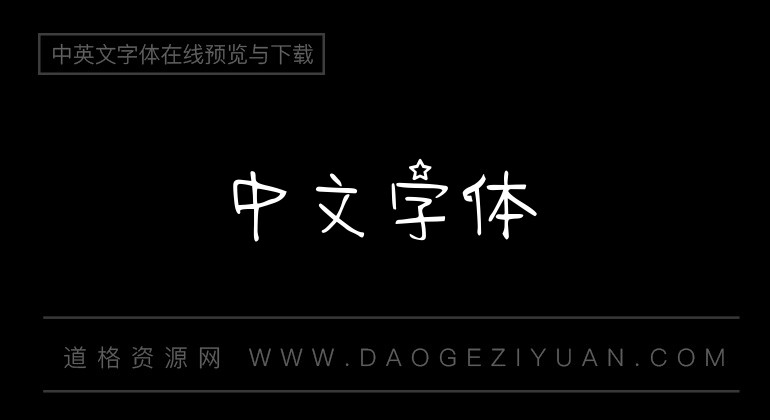
Aa最好的礼物就是一套定制字体,它可以根据用户的需求,让字体设计更灵活,更有个性化。这样的字体可以根据用户的偏好,提供丰富的字体设计,以满足不同的需求。此外,它还可以提供丰富的文字设计,让文字更加美观大方,以突出文字的特色。文件名:AaZuiHaoDeLiWu-2.ttf
Aa最好的礼物是一款非常不错的手写艺术字体,具有很好的视觉感,适合于文化类的宣传设计、商业类品牌的广告和产品包装设计以及个性化文字排版等较多场景。